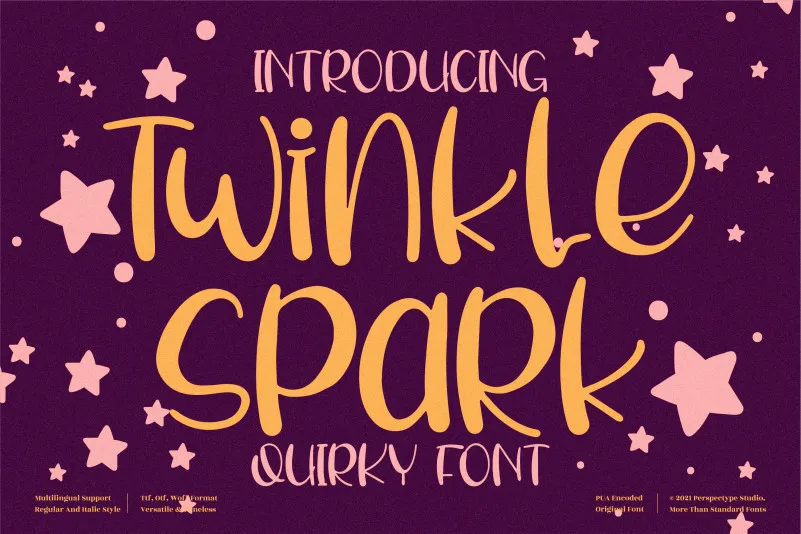
A Twinkle Spark Font é uma escolha perfeita para designers buscando uma fonte com estilo descontraído e encantador. Desenvolvida por perspectype, essa brush font apresenta um traço script único que se destaca no seu acervo de fontes. Com uma temática leve e alegre, esta font pode ser usada em vários tópicos, tornando-se uma incrível adição ao seu banco de fontes. Seja para gráficos digitais, logomarcas ou até mesmo design editorial, essa brush font é capaz de dar um toque especial à sua criação. Não importa o que você criar, a Twinkle Spark Font certamente enriquecerá e dourará cada projeto.